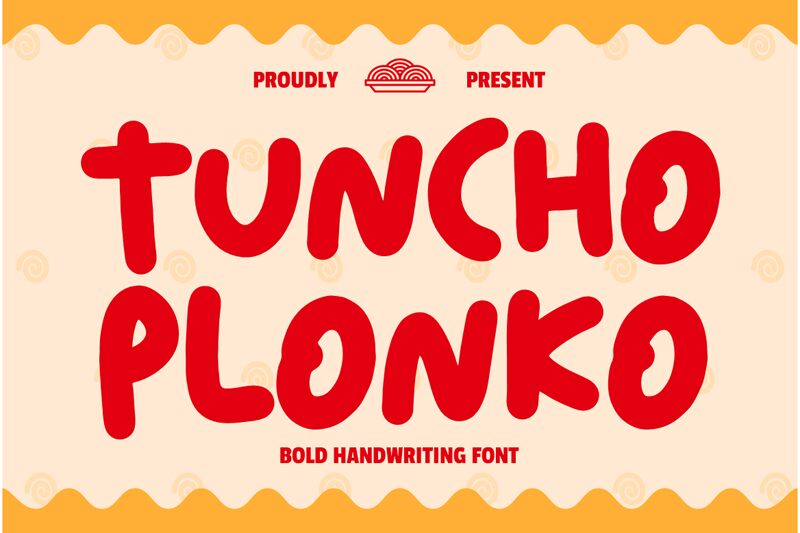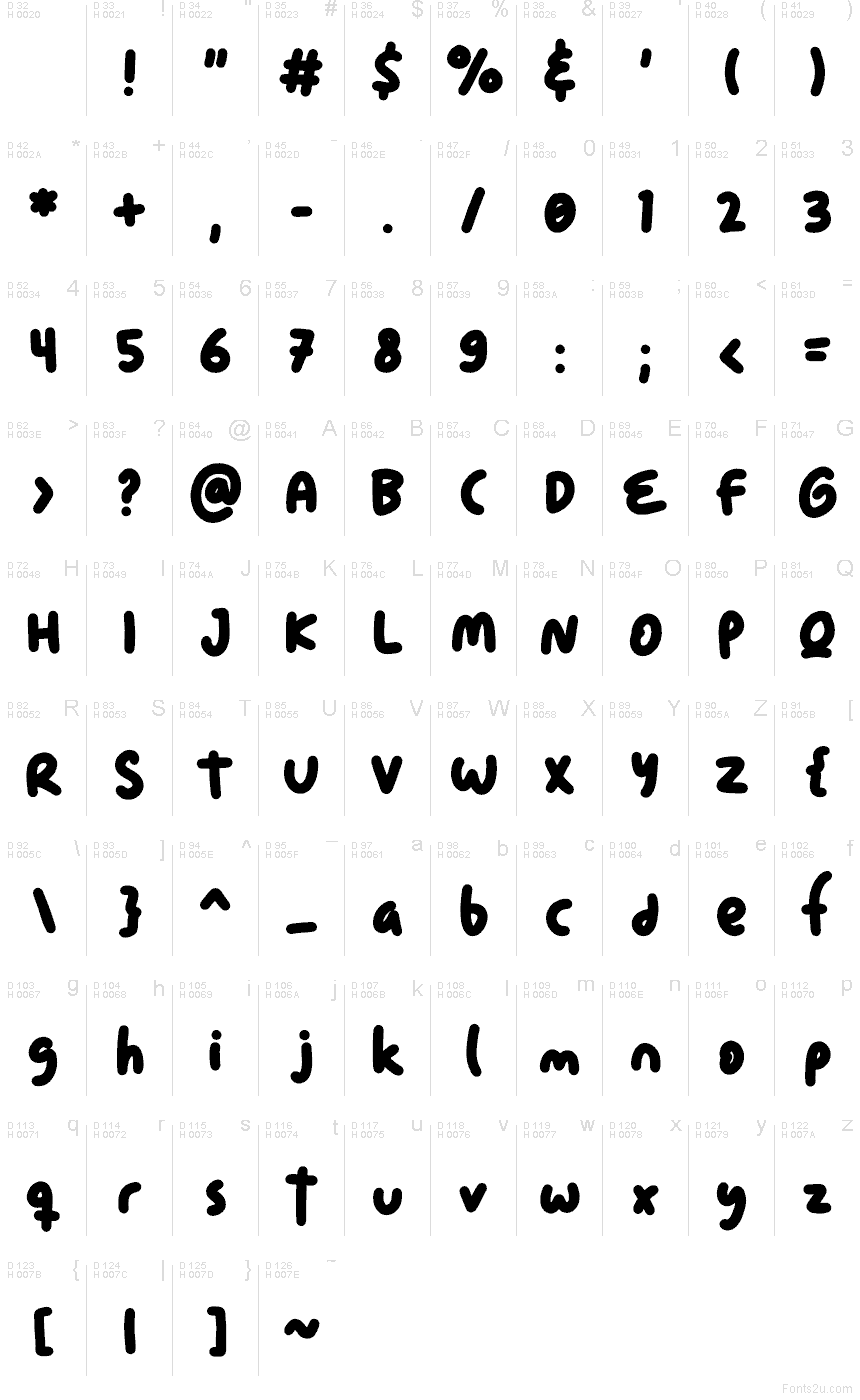
Tuncho Plonko
Tuncho Plonko, da Shanaf Studio, é uma fonte gratuita estilo comic, borbulhante e com um toque suave e saltitante. As letras transmitem uma sensação amigável e desenhada à mão, com terminações arredondadas, curvas volumosas e um ritmo ligeiramente irregular que torna o design divertido e autêntico, fugindo do visual muito polido.
É perfeita para branding infantil, embalagens de snacks, convites de festas, autocolantes e posts alegres nas redes sociais, onde palavras curtas pedem um tom carismático e descontraído. Como fonte gratuita, também funciona muito bem para títulos, logótipos simples e posters, já que as suas formas gordinhas e o espaçamento relaxado dão a qualquer texto um toque animado e leve.